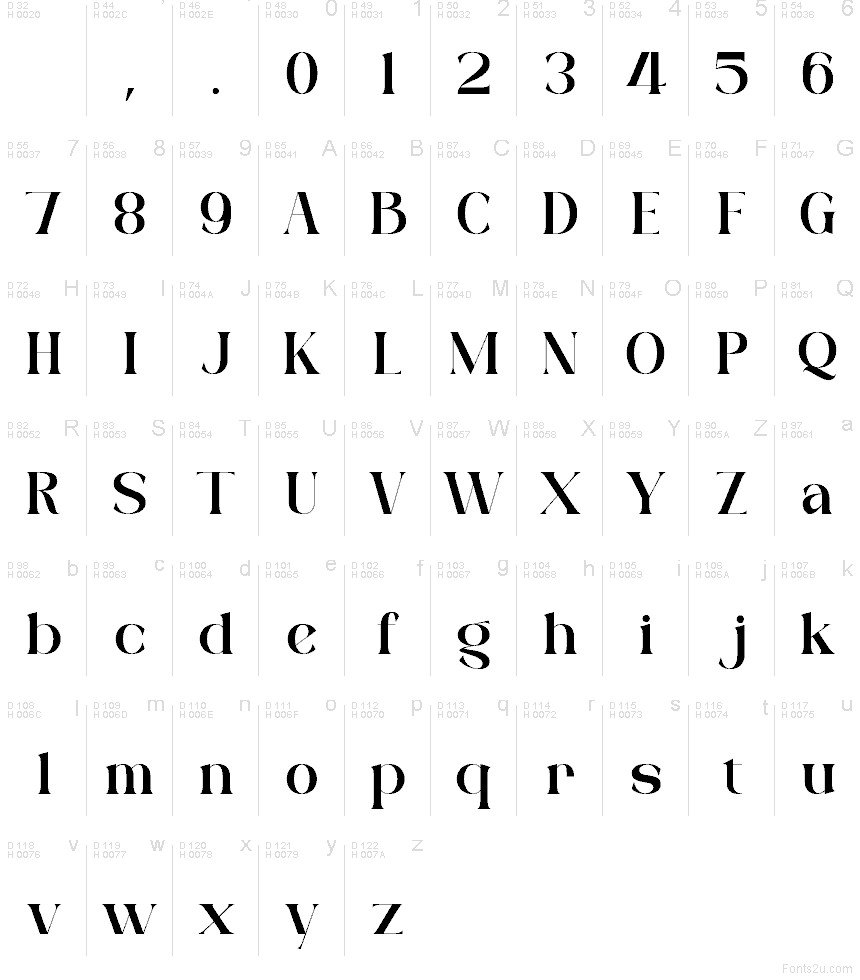
Rosavine هو خط Serif مجاني وعالي التباين من Muksal Creative، يوازن بين الأقواس المستديرة العريضة والوصلات الدقيقة للغاية والنهايات الحادة التي تشبه الإسفين. يمنح هذا المزيج الحروف إيقاعاً لامعاً وأنيقاً، حيث تبدو المنحنيات ممتلئة وسلسة بينما تمنع الضربات الزاوية الخط من أن يبدو ليناً أكثر من اللازم.
يبدو هذا الخط مثالياً في تغليف منتجات التجميل، وشعارات المتاجر الفاخرة، وعناوين المجلات، ودعوات الزفاف، وتصاميم وسائل التواصل الاجتماعي حيث تكون الصورة الظلية الراقية هي المحور. إنه مثالي للعناوين المختصرة ونصوص العرض، حيث يضفي التباين القوي والتفاصيل المدببة الدقيقة حضوراً رصيناً وفاخراً حتى على بضع كلمات فقط.